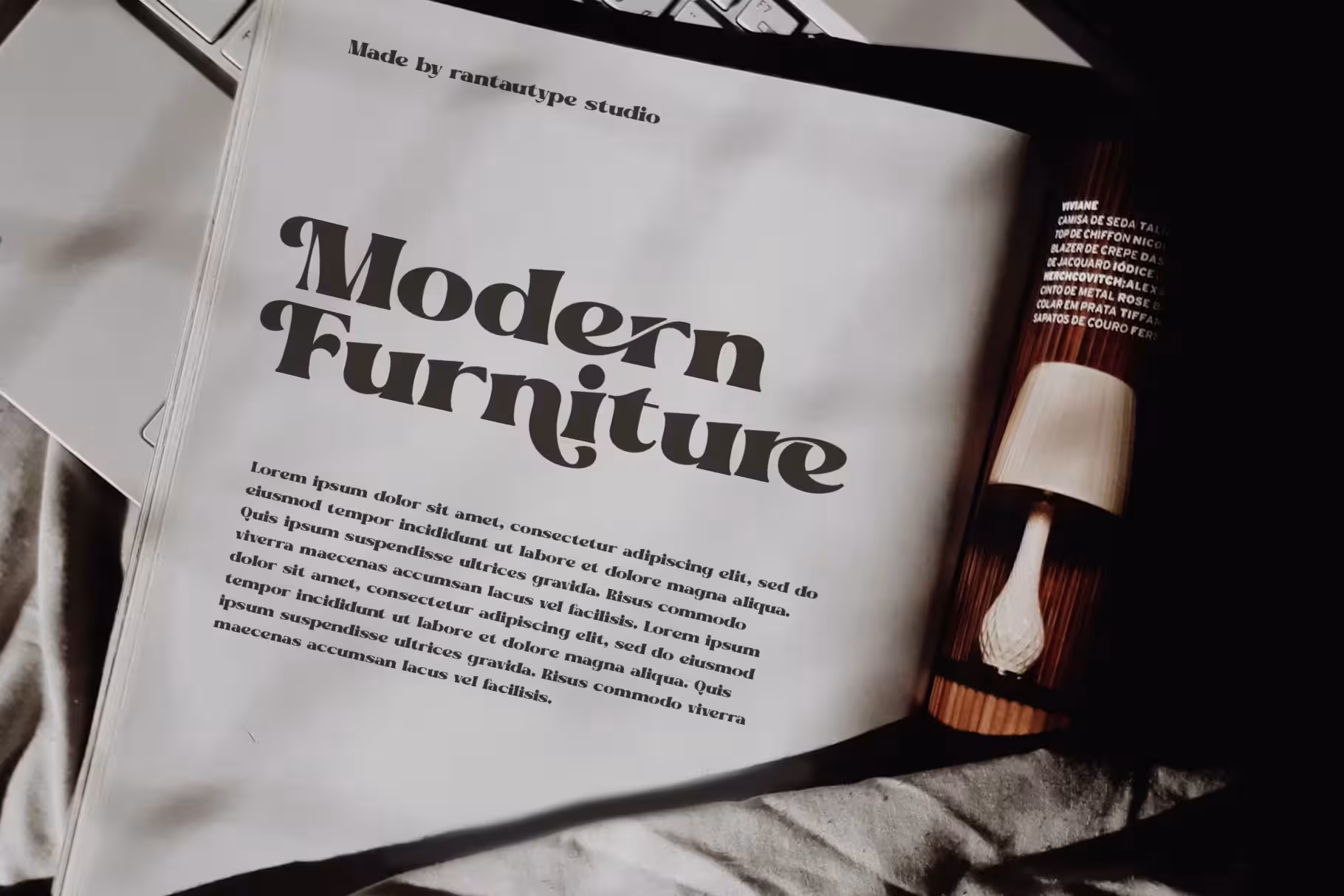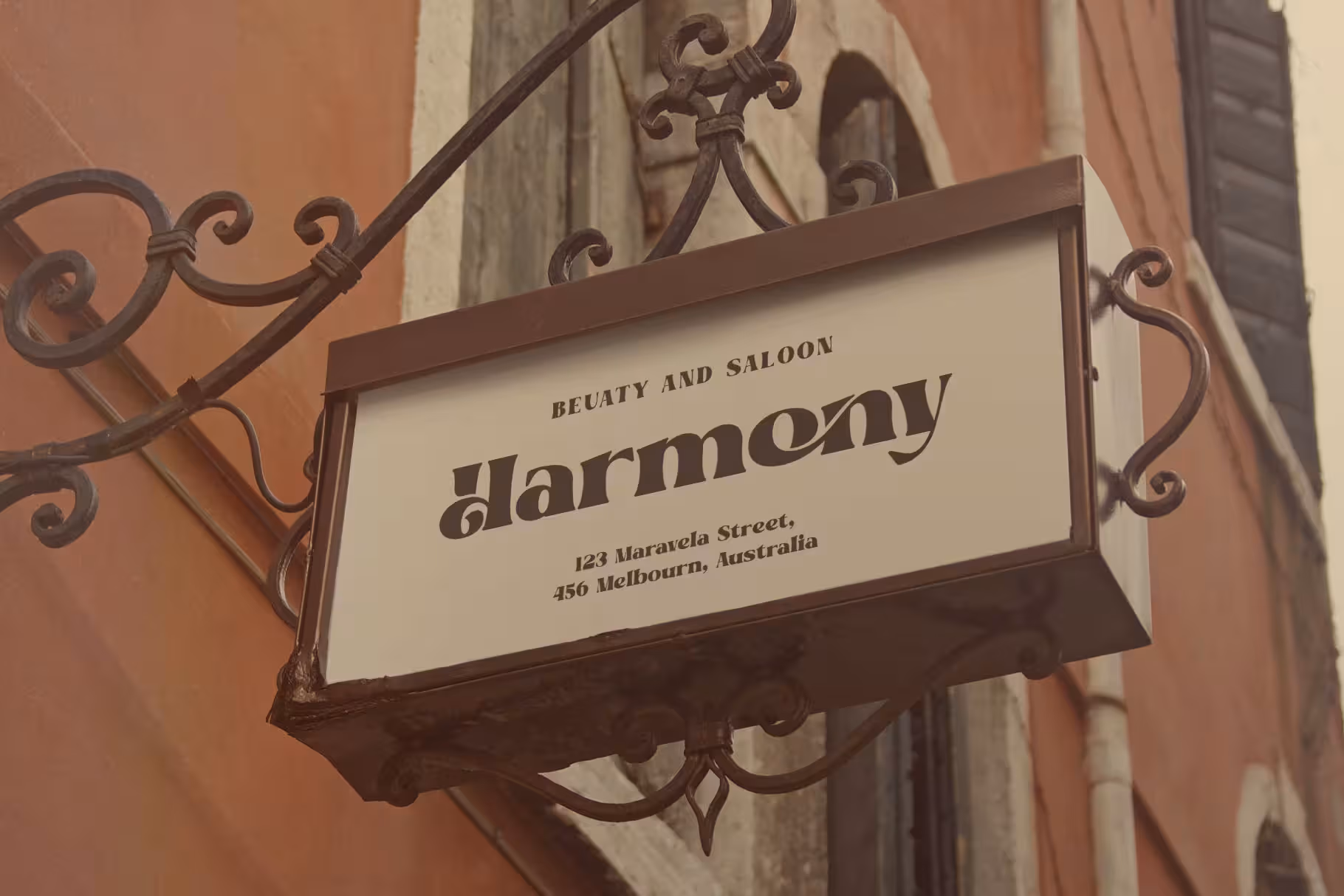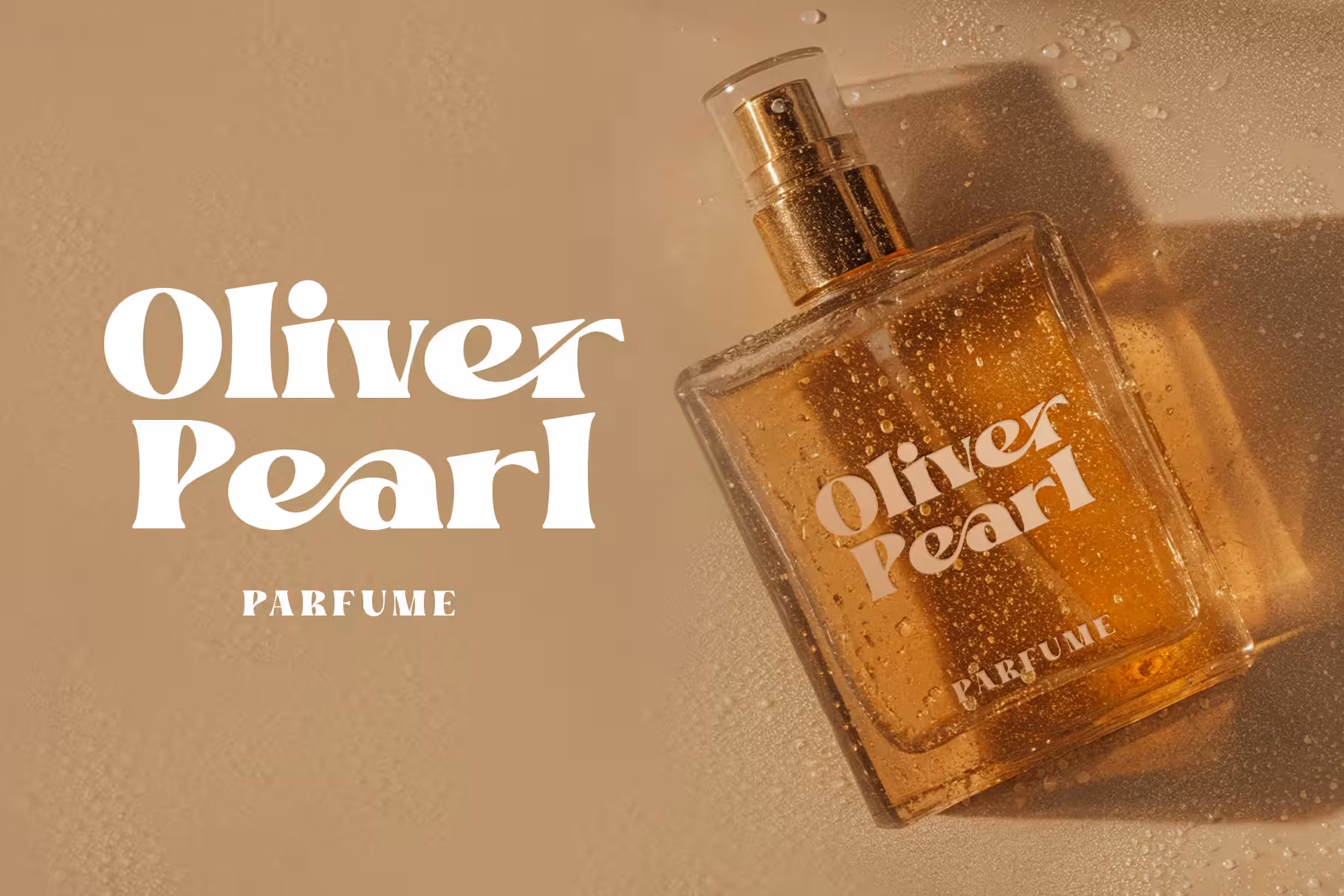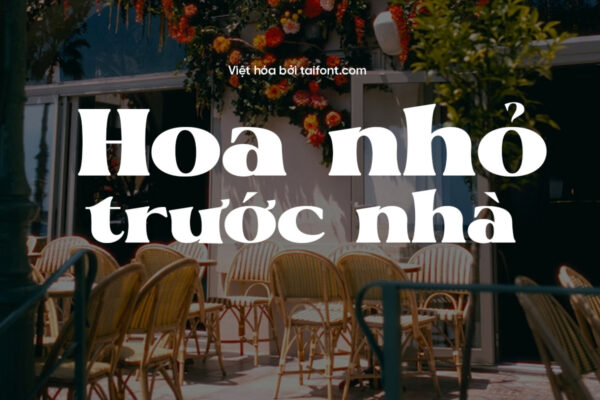
Giới thiệu về Font TF Halidary Việt hóa
TF Halidary Việt hóa là một font chữ nổi bật với vẻ đẹp sang trọng, tinh tế và đầy quyến rũ, lý tưởng cho các thiết kế đẳng cấp. Font này toát lên sự thanh lịch, mềm mại nhưng vẫn giữ được sự rõ ràng và chuyên nghiệp, phù hợp để tạo nên sự độc đáo và thu hút mọi ánh nhìn.
Với sự tinh xảo trong từng ký tự và tính thẩm mỹ vượt trội, Halidary là lựa chọn hoàn hảo cho các ấn phẩm cần sự sang trọng và khác biệt, đặc biệt là trong các lĩnh vực:
- Thiết kế mỹ phẩm: Hoàn hảo để sử dụng trên bao bì sản phẩm, nhãn chai, hoặc các chiến dịch quảng bá mỹ phẩm cao cấp. Font này giúp khẳng định chất lượng, sự sang trọng và vẻ đẹp tinh túy của sản phẩm, thu hút ánh nhìn của khách hàng và truyền tải thông điệp về sự quyến rũ, đẳng cấp.
- Thiết kế nước hoa: Lý tưởng để sử dụng trên bao bì sản phẩm, nhãn chai hoặc các chiến dịch quảng bá nước hoa. Halidary giúp sản phẩm toát lên sự quý phái, độc quyền và đầy mê hoặc.
- Thiết kế tạp chí: Phù hợp để sử dụng cho các tiêu đề chính, lời dẫn, hoặc nội dung bài viết trong các tạp chí về thời trang, làm đẹp, hoặc phong cách sống. Nét chữ của Halidary giúp tăng tính trang trọng và dễ đọc, đồng thời tạo cảm giác cao cấp, thu hút độc giả.
- Thiết kế nhận diện thương hiệu: Lý tưởng cho logo, tagline hoặc bộ nhận diện thương hiệu muốn truyền tải sự tinh tế, uy tín và sự thanh lịch. Halidary giúp xây dựng một hình ảnh thương hiệu vững chắc và dễ nhận diện.
Với TF Halidary Việt hóa, bạn có thể dễ dàng thổi hồn tinh tế, sang trọng và vẻ đẹp hoàn hảo vào các thiết kế, tạo ra những sản phẩm không chỉ đẹp mắt mà còn đầy cảm xúc và sức hút đặc biệt.